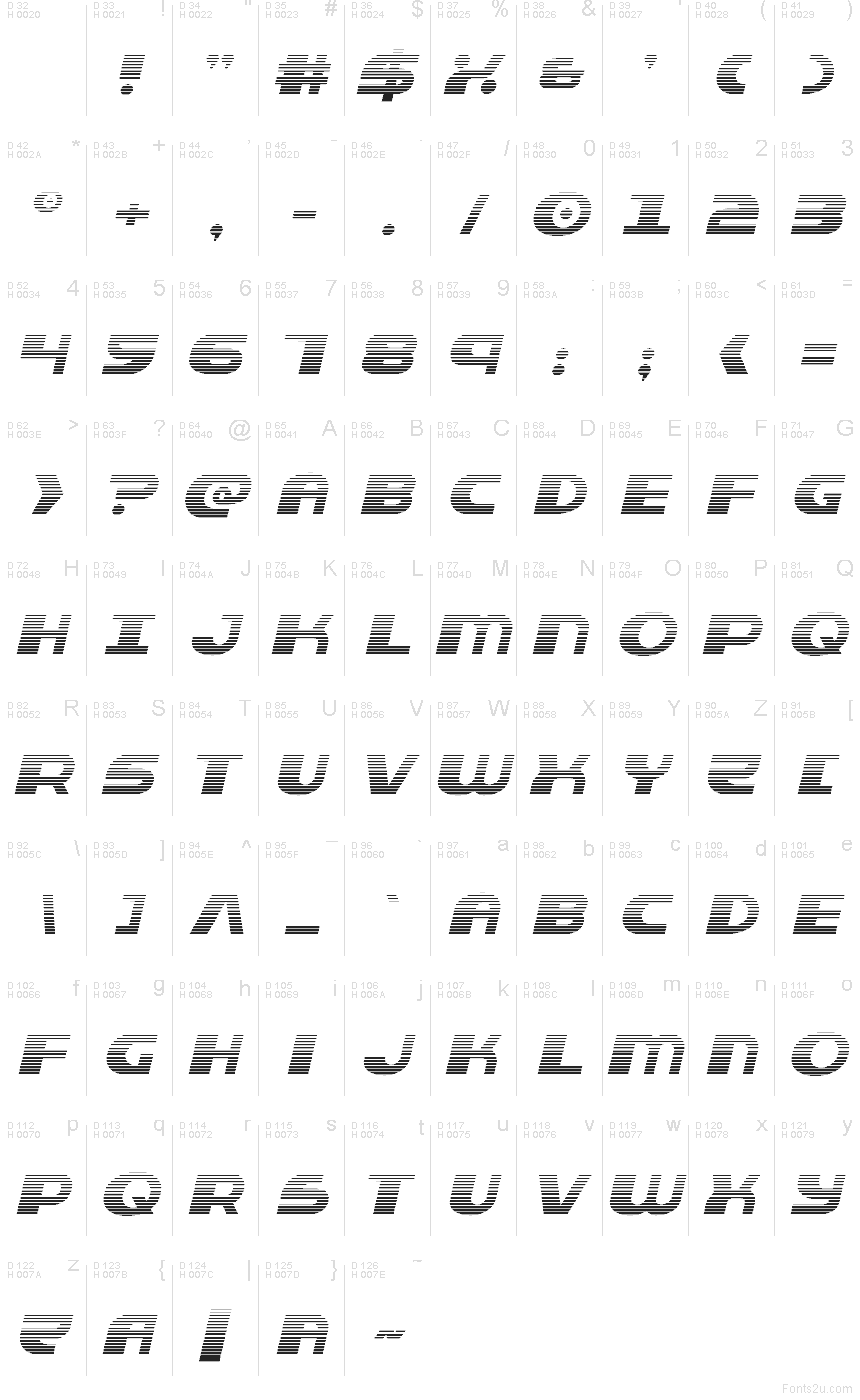
Dashiel Gradient Italic od Iconian Fonts to darmowy, kursywny krój akcydensowy z efektem pasków prędkości, utrzymany w retro-futurystycznym, wyścigowym klimacie. Wielkie litery pochylają się do przodu, tworząc szerokie, blokowe formy przecięte poziomymi pasami. Dzięki temu całość przypomina bardziej grafikę z gier arcade lub logotypy sportowe w stylu science-fiction, niż zwykłe, pochyłe pismo.
To świetny, darmowy wybór do plakatów, brandingu gier, nagłówków, okładek i logotypów drużyn, gdzie liczy się szybki, syntetyczny wydźwięk. Krój najlepiej sprawdza się w krótkich napisach, ponieważ efekt pasków nadaje nawet prostym słowom poczucie ruchu i lekko mechaniczny charakter.